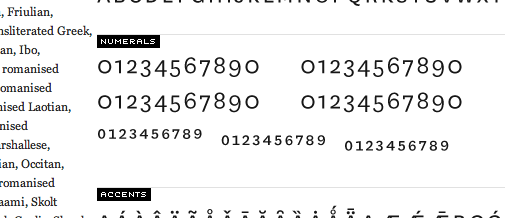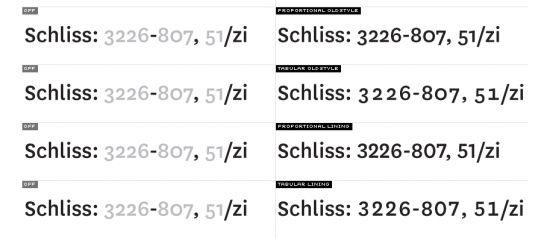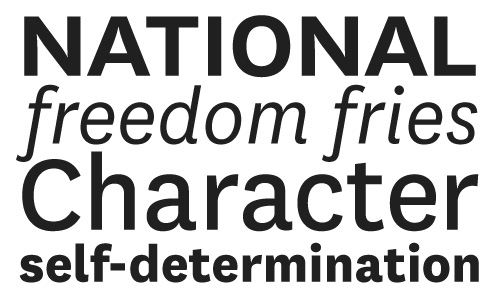
National (KLIM/Village)
National is a deceptively simple sans serif with subtle quirks in the details
that give it a distinctive—but not distracting—personality. While National
travels through, and touches on, a lot of historical material, it is designed
to thrive in our modern typographic climate. National’s details are drawn
from the best pre-Akzidenz grotesques, giving it a humble, workmanlike
character with an agreeable tone of voice. Its extensive character set
includes a wide array of accents, seven numeral sets, alternate forms for
some base glyphs, and small caps across all styles. In short, all the good
things that the exacting typographer should expect from a contemporary
OpenType typeface.
Ich finde die Kursive auch besonders hübsch - aber auch die ganze Schrift hat was. So traditionell und gleichsam modern, sehr sorgfältig abgewogen, dabei gar nicht "trendy".
Ob man die auch gut als Korrespondenzschrift verwenden kann?
Sehr schön, ob dick ob dünn, besonders die Italic.
Eine Antwort (?) versteckt sich im Blindtext des Schriftmusters:
Nationalist movements see themselves as the representative
of an existing, centuries-old nation. However, some theories
of nationalism imply the reverse order—that the nationalist
movements created the sense of national identity, and then a
political unit corresponding to it, or that an existing state
promoted a ‘national’ identity for itself.
Leider hält der deutsche Vorschautext nicht, was hier besprochen wurde. Woher er die Menschenrechtscharta kopiert hat, ist mir ein Schleier, aber ein Typespecimen, wo man mich mit »beßere Lebensbedingungen« zu überzeugen versucht, hat es schwer. Ich glaube ja, dass Übersetzer ein ähnlich schweres, missachtetes Leben haben wie Typedesigner. Schlimm, wenn die einen die anderen dann so enttäuschen.
Also, die ganze Zahl nur auf Mittelhöhe? Wofür braucht man das? Wissenschaftstexte?
Oder sind's die ganz kleinen Ziffern?
Also, die ganze Zahl nur auf Mittelhöhe? Wofür braucht man das? Wissenschaftstexte?
Oder sind's die ganz kleinen Ziffern?
z.b. im fliesstext von geschäftsberichten. als alternative zu den doch etwas unruhigen minuskelziffern.
Naja, bis auf die Kursive finde ich es schon ein ziemliches sample von Bau und Akkurat. Wenn auch ein preiswertes.
Schelter & Giesecke revisiting liegt wohl gerade in der Luft.
z.b. im fliesstext von geschäftsberichten. als alternative zu den doch etwas unruhigen minuskelziffern.
Je nach Gestaltung der Minuskelziffern finde ich sie manchmal auch nicht ganz passend zu den Kapitälchen-Buchstaben, da sie durch die Ober- und Unterlängen das "bandartige" der Kapitälchen eigentlich zerstören. Und Vesalziffern sind wiederum zu groß...
Je nach Schrift sind die Minuskelziffern natürlich auch oft unauffällig genug.
Ich finde die SC-Ziffern besonders bei Adresseblöcken auf Visitenkarten oder Briefbögen, die in den
schönen SC-Schnitten gesetzt sind (weil man z.B. keine Lust auf den wuchtigen Versalsatz hat) sehr brauchbar.
Die COMPATIL hat z.B. SC-Ziffern, aber keine Mediävalziffern, was ich sehr ungewöhnlich finde.
Christoph
der euro steht ja verdammt gut, ich glaube ich kann da nicht wiederstehen und
hole mir das gesamte paket. hat sie schon jemand getestet und kann was über
die technischen eigenschaften sagen? kerning? wie erscheint sie im schriftenmenü?
als kompletter zeichensatz mit untermenü oder als einzelfonts wie die schriften von
ds-type?
keine ahnung aber ich habe auch schon überlegt ob ich sie kaufe. allerdings
ist das angebot schon wieder so günstig das ich direkt skeptisch werde ...
herr dos santos hat übrigens auch eine auszeichnung beim tdc erhalten –
trotz der teilweise mangelnden qualität!
:evil:
ich habe sie gerade mal mit der akkurat verglichen und ich finde sie um einiges schöner als die akkurat, sie ist viel dynamischer. wenn ich mir dann noch die ganzen, gut ausgebauten, schnitte und alternates anschaue ... RRRR!
in der page habe ich ein kleines bild der 'akkurat black' gesehen wenn sie es denn mal sein/werden soll, dass hat mir irgendwie gar nicht gefallen. aber soviel war da auch nicht zu sehen das man sich da jetzt schon ein urteil bilden könnte.
Kris Sowersby halte ich für einen sehr fähigen Typedesigner - nicht umsonst
hat er zusammen mit Spiekermann und Schwartz an der Meta Serif gearbeitet.
Allerdings ist er eine Ein-Mann-Foundry und die Möglichkeiten was das Testen
der Fonts anbelangt sind begrenzt. Ralf hat das schon einmal sehr anschaulich
beschrieben und seit dem bin ich bei kleineren Foundrys vorsichtiger geworden.
Siehe Herrn dos Santos ...